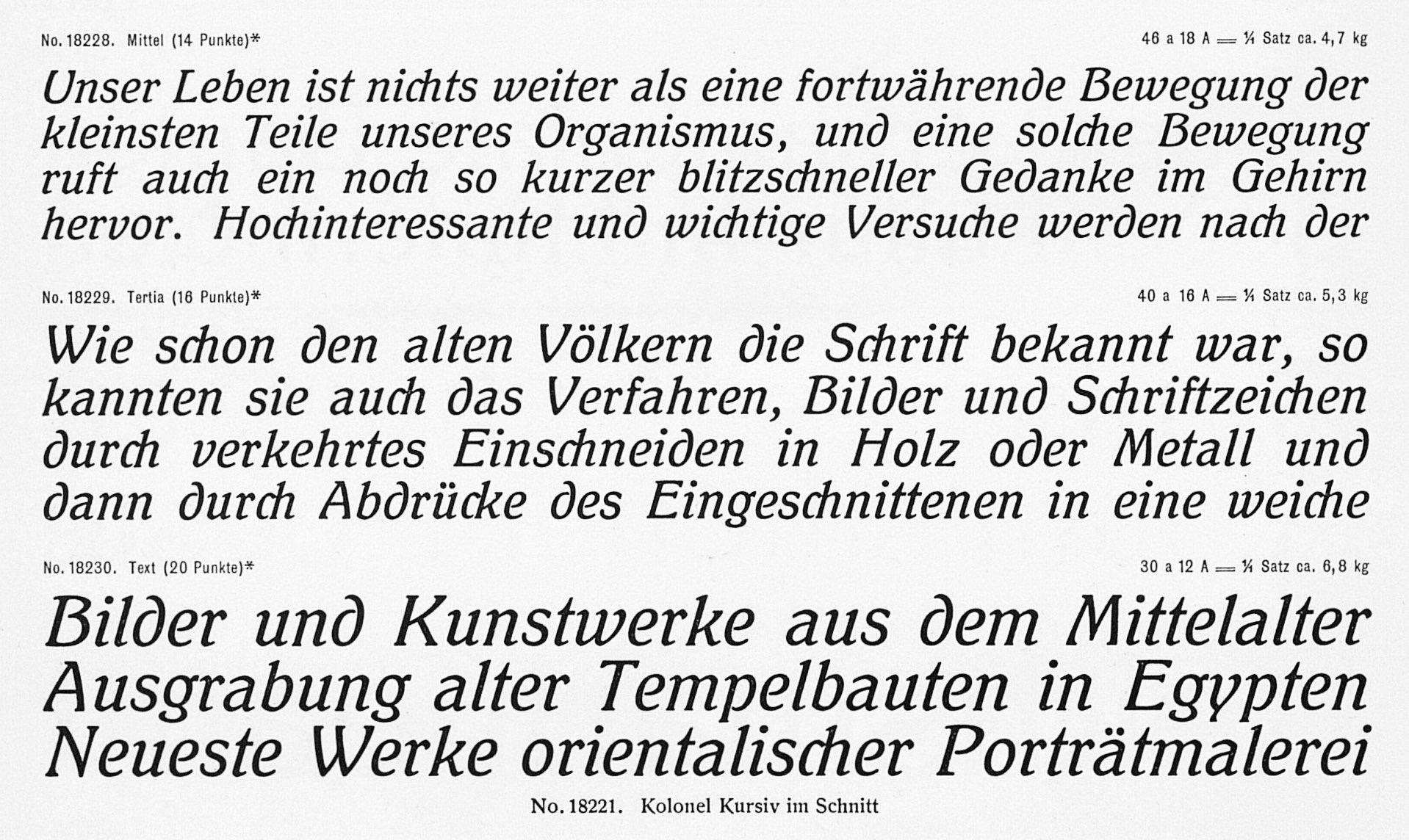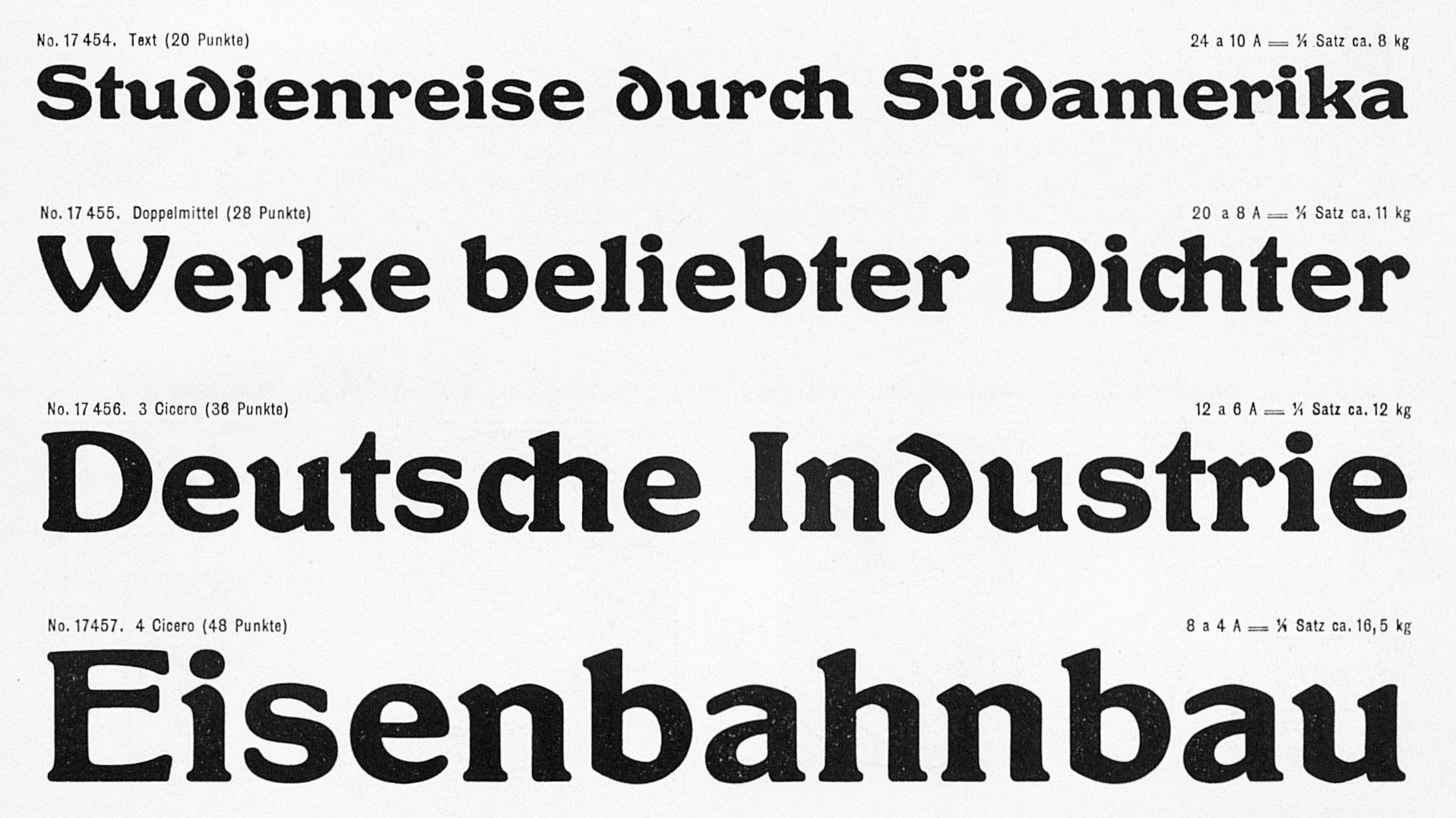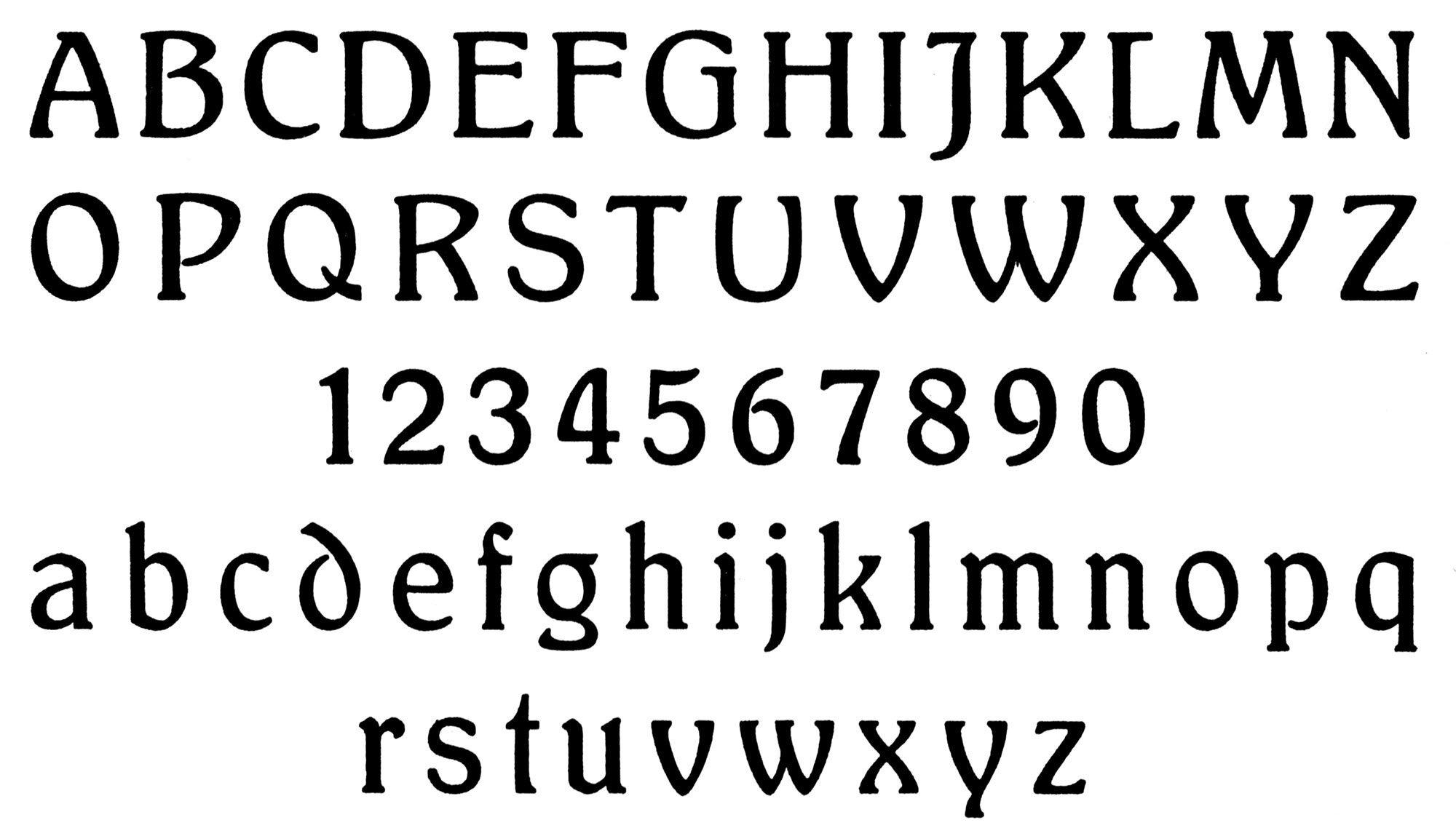
- 1905
- Antiqua humanistisch
- Versaleszett:
- enthalten
Die Schelter-Antiqua ist eine Schriftfamilie mit Hausschnitten der Schriftgießerei Schelter & Giesecke und erschien Anfang des 20. Jahrhunderts.
»Mit unserer Schelter Antiqua, die wir so zu Ehren des Mitbegründers der Firma: Johann Andreas Gottfried Schelter benennen, übergeben wir der Öffentlichkeit eine neue Schriftfamilie, deren Grundtype, die Buchschrift, von uns durch Zuschnitt einer Kursiv, einer halbfetten, einer breiten halbfetten und einer schmalen halbfetten Schrift erweitert und ergänzt wurde. Wir bieten hiermit dem Fachmann wiederum eine geschlossene Schriftserie, die ihm gestattet, seine Druckarbeiten in einheitlicher stilgerechter Weise durchzuführen … Die Schelter-Antiqua, die in ihren verschiedenen Verbreiterungen, Verdickungen und Schrägformen einen Schatz von etwa siebzig verschiedenen Schriftgrößen darstellt, bedeutet unseres Erachtens einen Fortschritt auf dem Wege, das eine Zeitlang verloren gegangene Verständnis für die Betrachtung jedes einzelnen Schriftzeichens als konstruktives Ganzes wieder zu gewinnen.«